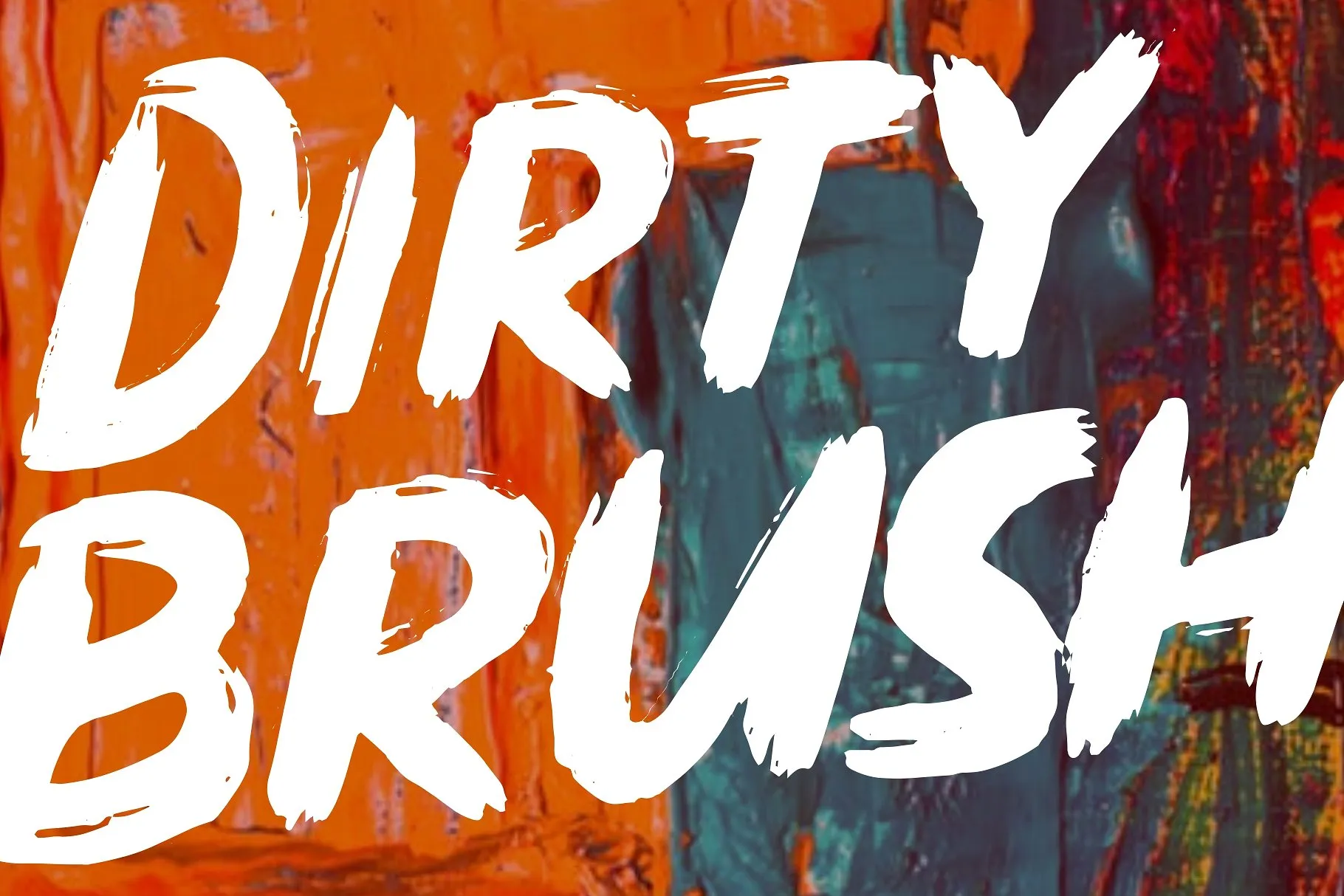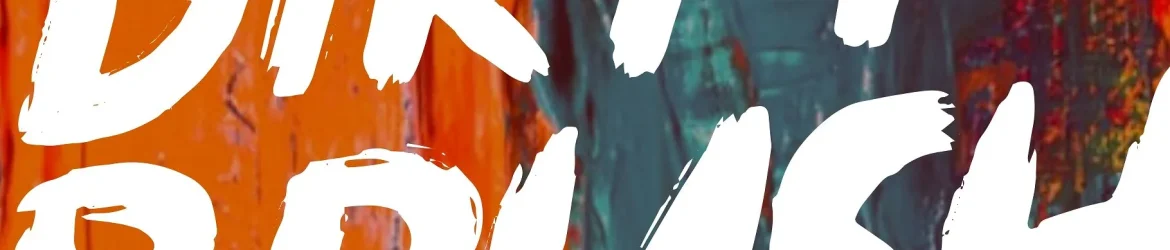
A fonte ‘Dirty Brush Font’ é uma tipografia script que combina elegantes curvas com um toque urbano moderno. Ideal para criar logos, imagens de marca e textos escritos a mão, essa fonte oferece uma aparência irresistivelmente atraente. Ela também se destaca em design de embalagens, materiais promocionais e postagem nas redes sociais. A ‘Dirty Brush Font’ é um must-have para quem busca combinar personalidade com sofisticação no seu trabalho visual. Uma fonte ideal para aqueles que desejam dar um toque único à sua identidade de marca ou ao design gráfico.